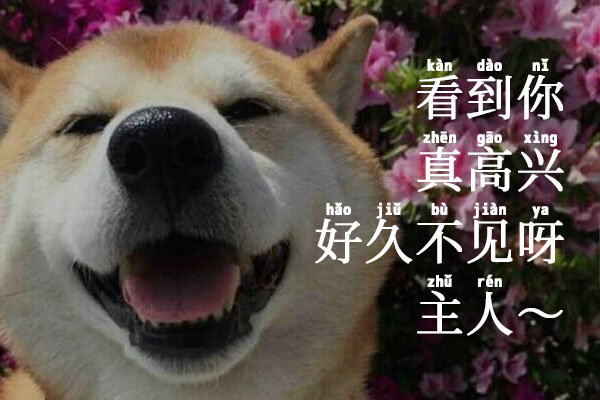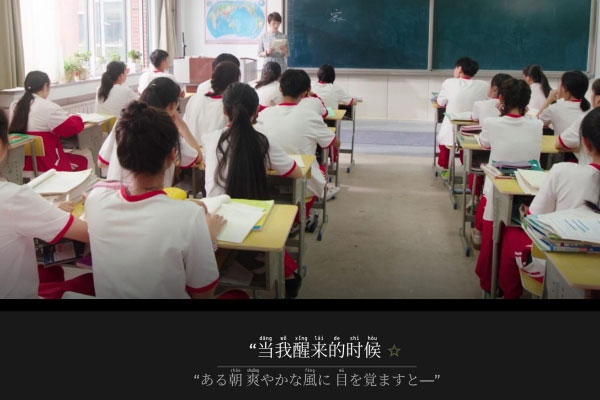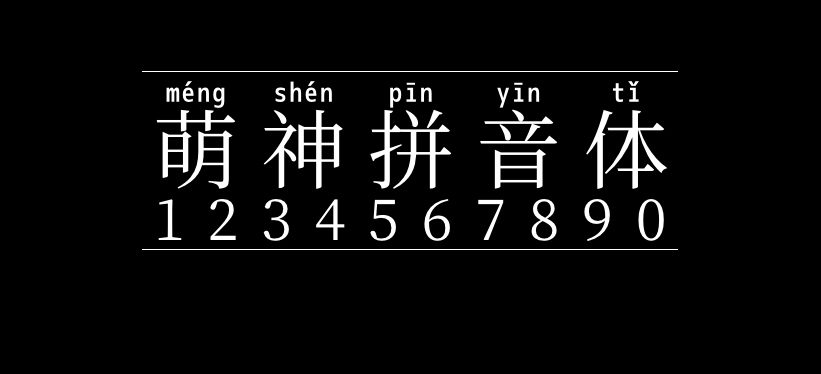
萌神拼音体
萌神拼音体(mengshen)是日本MaruTama开发的一款用于学习中国汉字的字体,使用思源宋体和M+字体进行改造而成的一款免费商用字体。 这是一种用来帮助学生更快地学习和阅读汉语的字体。在某些设计场景其实也挺实用的,特别是对教育类的设计比较有用。
由于是基于思源宋体的,所以对简体字和繁体字的支持都比较全,很少出现缺字的情况,字重只有一种所以字体包文件也比较小。